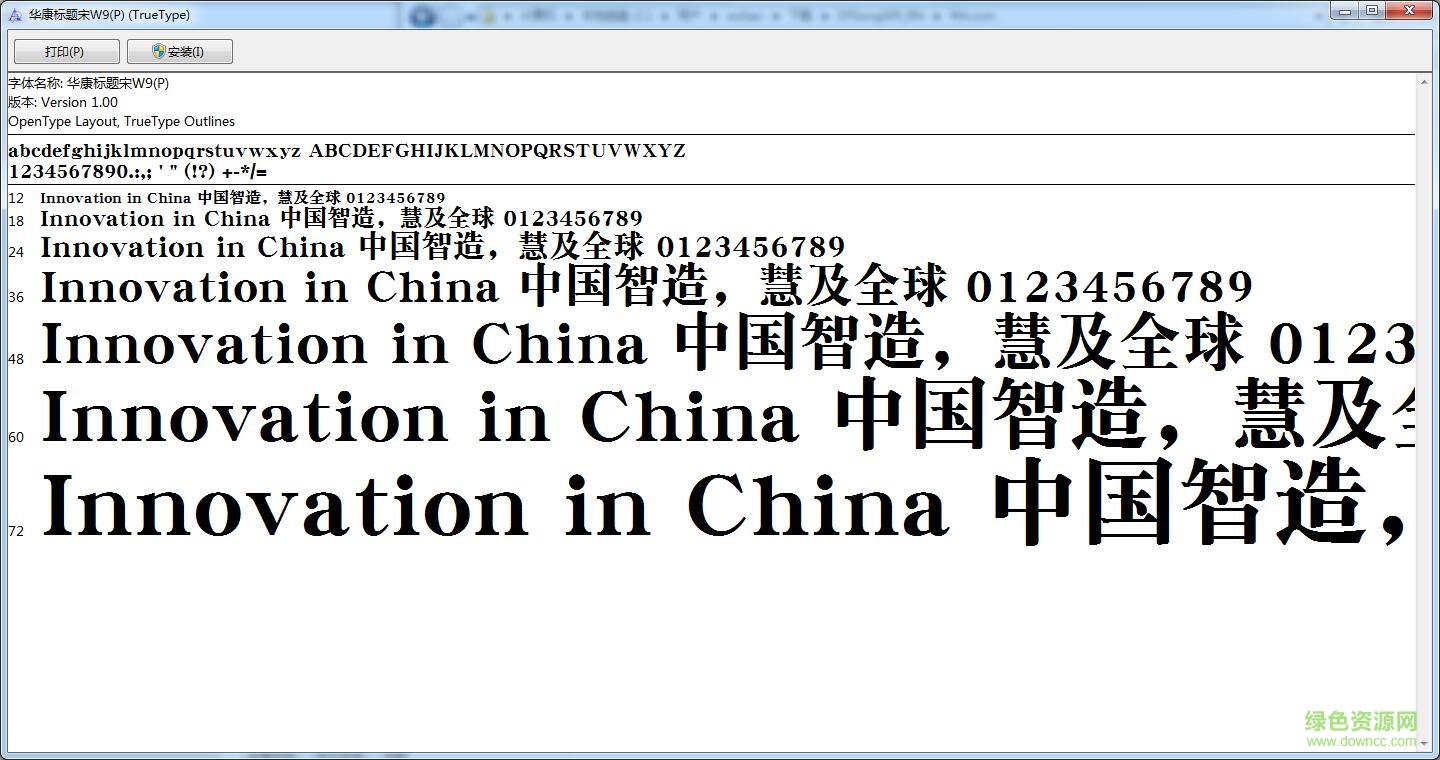
dfpsongw9是什么字體?dfpsongw9 regular字體又叫華康標(biāo)題宋w9(p),該字體結(jié)構(gòu)嚴(yán)謹(jǐn),行筆輕重交錯(cuò),典雅大氣,閱讀性很高,常常用于文章標(biāo)題,有需要者快來綠色資源網(wǎng)下載吧!
宋體字于明朝以后才出現(xiàn),那何以謂作“宋體”?原來,明朝出版界多翻刻宋本,但為求便捷,這些仿宋刊本經(jīng)常只刻出“膚廓字樣”,而非原來楷味濃厚的字??滴跏辏吠⒊佳a(bǔ)刊經(jīng)庵《文獻(xiàn)通考》的序文中,規(guī)定:“此后刻書,凡方體稱宋體字,楷書均稱軟字”?!八误w”之名,乃清朝康熙皇帝指定。